Logo & custom typeface for Lov3, Amazon Prime Video.
Lov3 é uma série sobre o estado do amor e sexo hoje, sobre como, apesar de novos modelos e formatos de relacionamento, precisamos nos comprometer com algo—com os outros, com nós mesmos. Lov3 é a história de três irmãos que diante do fim do casamento de seus pais passam a reavaliar suas próprias escolhas afetivas.
Logo e tipografia buscam transmitir a autenticidade dos protagonistas. Com formato quadrado, representa força e constrói uma narrativa jovem e rock 'n' roll.
Lov3 is a tv show about the state of love and sex nowadays, about how despite new models and relationship formats we need to commit to something—to others, to ourselves. Lov3 is the story of three brothers who, facing the end of their parents' marriage, start to reevaluate their own love choices.
Logo and typeface seek to convey the authenticity of the protagonists. With a square shape, it represents strength and builds a young and rock 'n' roll narrative.
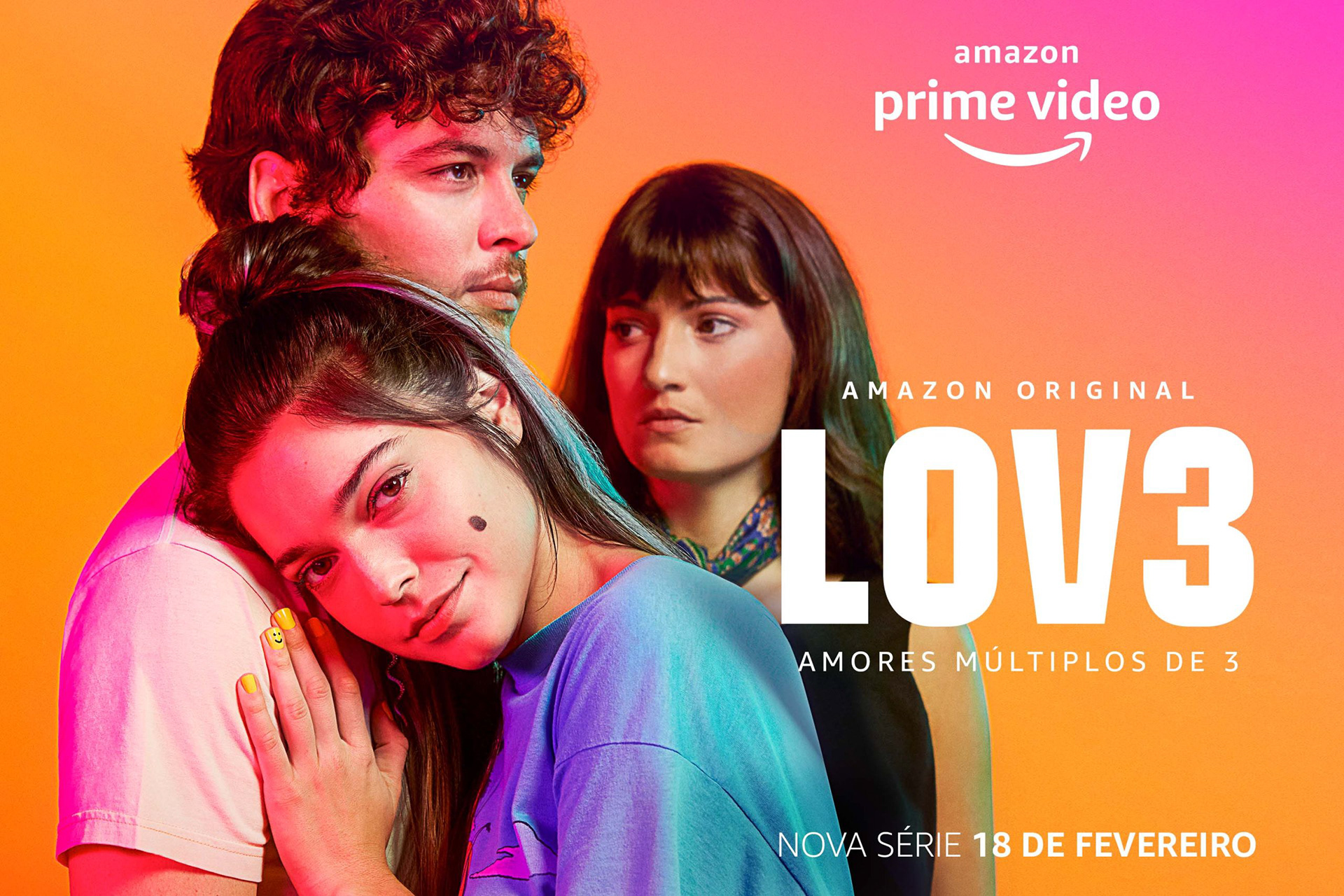
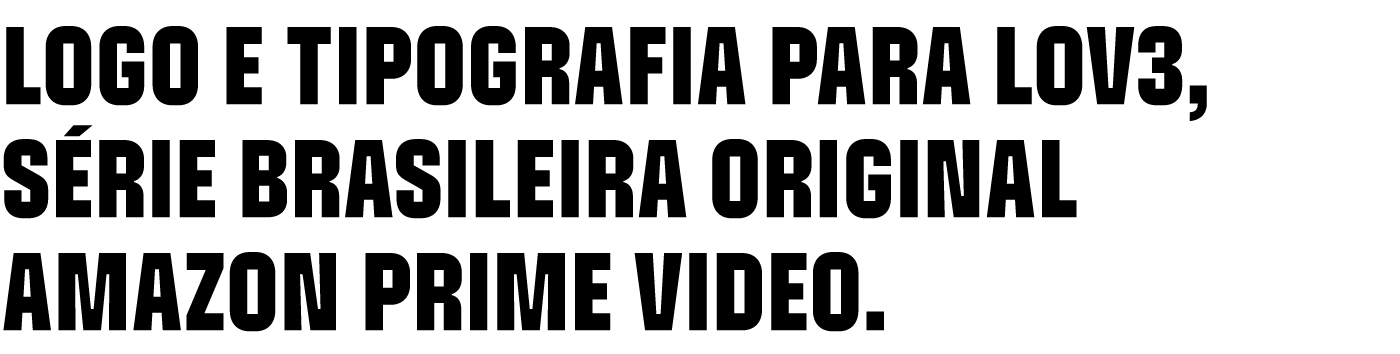
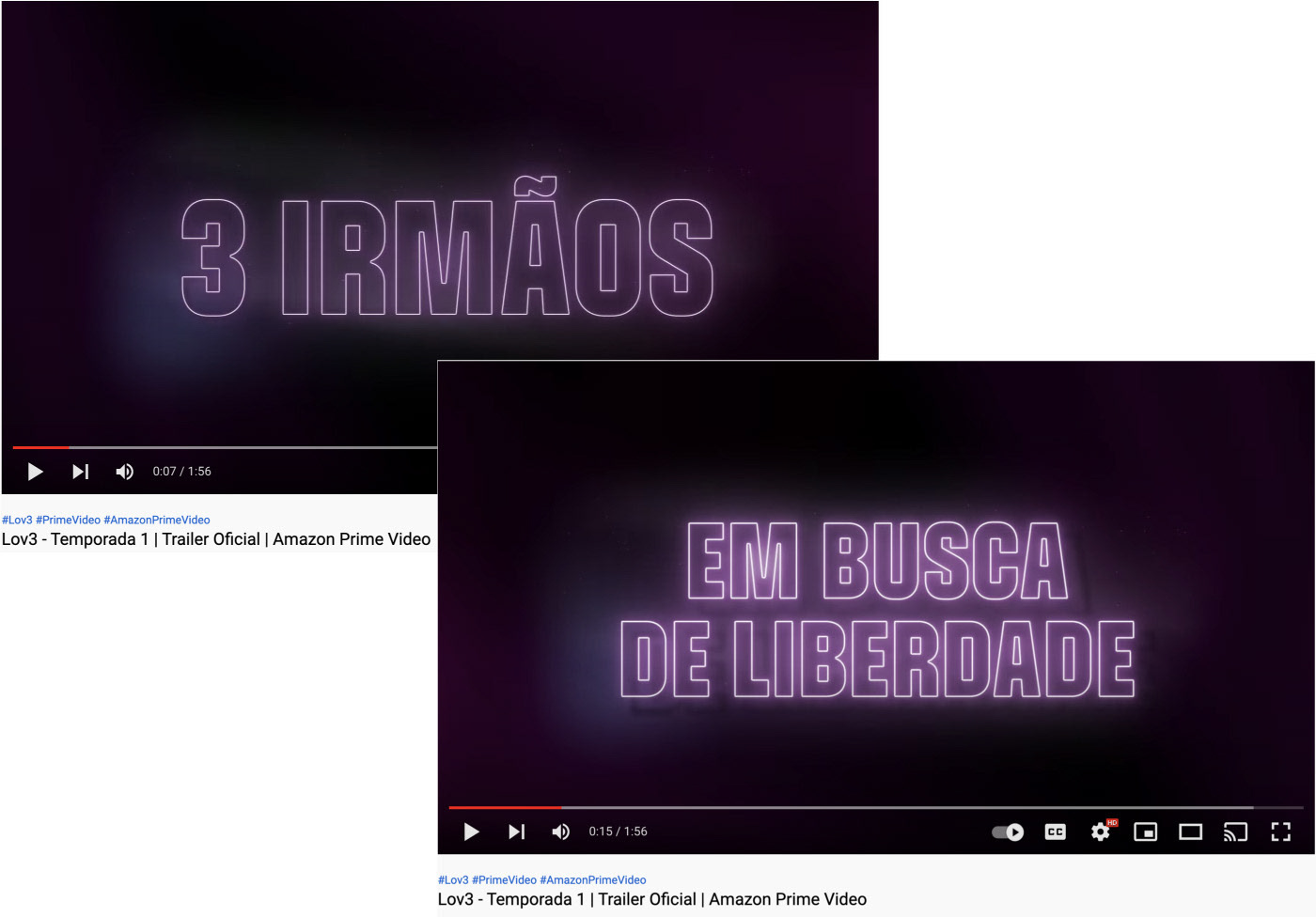
O logo possui duas versões. A versão aplicada a abertura dos episódios é mais pesada e comprimida, enquanto a versão usada na divulgação é mais leve e expandida. A intenção é gerar impacto na abertura e preservar a legibilidade em aplicações menores. Para definir a largura e peso mais adequados para cada situação foi utilizada a tecnologia Variable Font.
The logo has two versions. The one applied to the opening of the episodes is heavier and compressed, while the version used in the publicity is lighter and expanded. The intention is to generate an impact on the opening and preserve the legibility in smaller applications. To explore and define the most appropriate width and weight I used Variable Font technology.